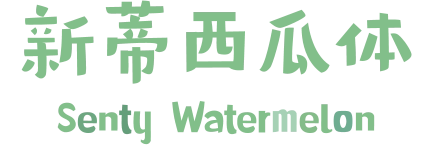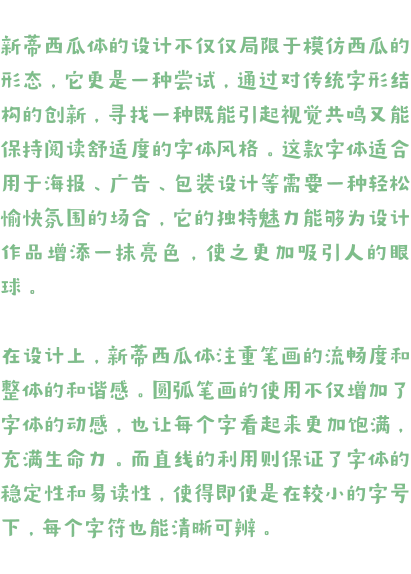
新蒂西瓜体 Senty Watermelon 新蒂西瓜体字体是一款富有创意和活力的字体设计,其设计灵感来源于西瓜的形状和质感。这款字体的特点在于它的笔画简洁而明快,圆弧和直线的结合 新蒂西瓜体的设计不仅仅局限于模仿西瓜的形态,它更是一种尝试,通过对传统字形结构的创新,寻找一种既能引起视觉共鸣又能保持阅读舒适度的字体风格。这款字体适合用于海报、广告、包装设计等需要一种轻松愉快氛围的场合,它的独特魅力能够为设计作品增添一抹亮色,使之更加吸引人的眼球。  在设计上,新蒂西瓜体注重笔画的流畅度和整体的和谐感。圆弧笔画的使用不仅增加了字体的动感,也让每个字看起来更加饱满,充满生命力。而直线的利用则保证了字体的稳定性和易读性,使得即便是在较小的字号下,每个字符也能清晰可辨。
恰似西瓜的轮廓,让人联想到夏日的清新和欢乐。笔画的圆润与直线的利落在视觉上形成了一种独特的对比,既展现了西瓜体的现代感,也保留了字体的易读性。 授权报价 Quick Quotation